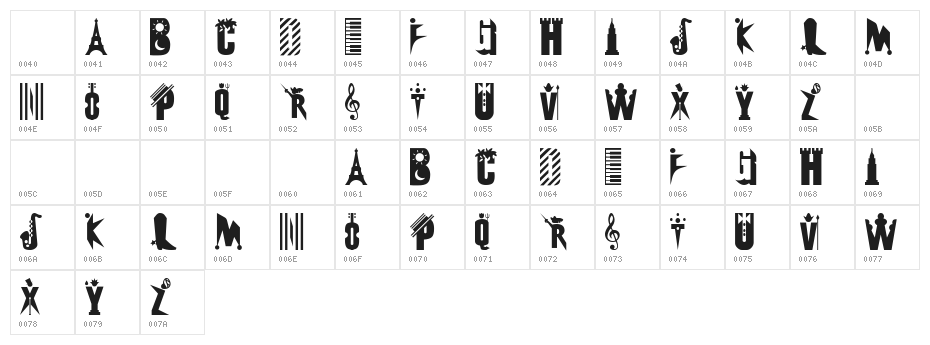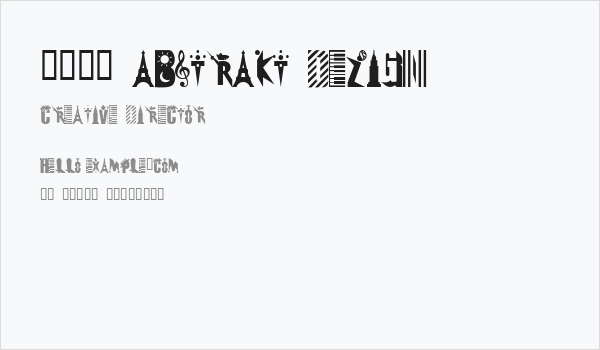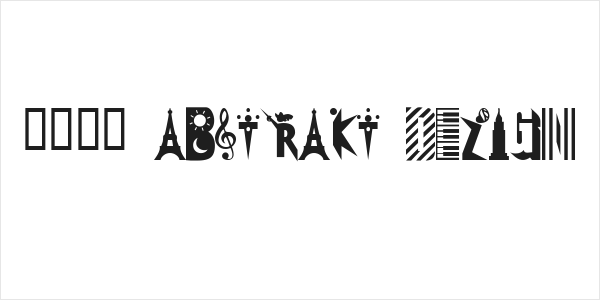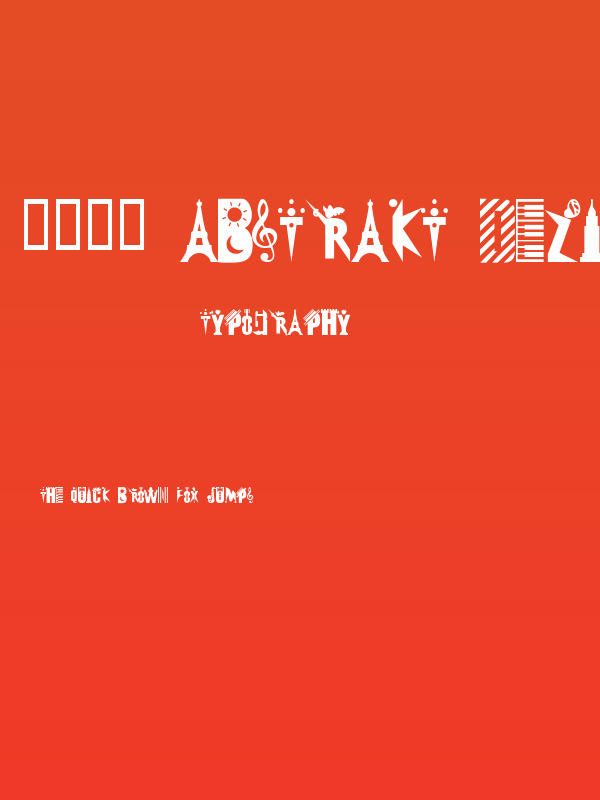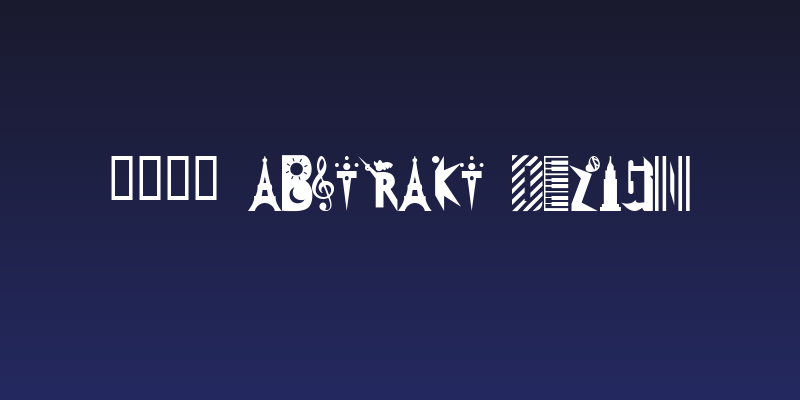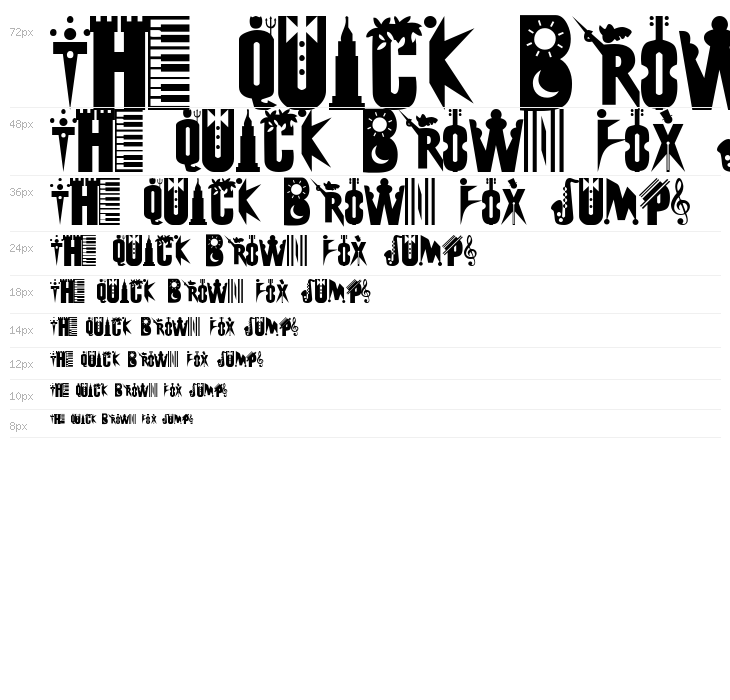
101! Abstrakt DeZign Font
| Caso d'uso | Headlines, Logos, Artistic projects |
| Progetti proposti | Ideal for creative projects, posters, album covers, and artistic branding that require a unique and eye-catching typeface. |